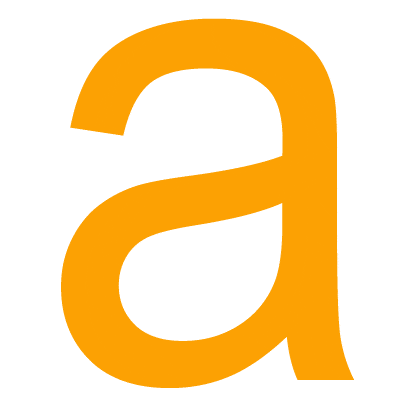
Arial (Sonora Sans)Uma família de fontes sem-serifa, de qualidade inferior. É conhecida entre os designers gráficos pela sua semelhança com um tipo famoso, a Helvetica.Sendo a Helvetica uma letra de estética bem árida, a Arial consegue ser uma cópia inferior da Helvetica. Supostamente, a Arial foi inspirada no desenho de uma outra fonte, a Hass Grotesk, (que também serviu de inspiração ao desenho da Helvetica). Esta fonte foi desenvolvida como uma fonte bitmap sem-serifa por Robin Nicholas e Patricia Saunders em 1982 nos escritórios da empresa Monotype no Reino Unido. A IBM já havia usado uma fonte similar, a Helvetica, adquirida à Linotype, na impressora IBM 4250. Mas talvez pelos elevados custos de licenciamento da fonte Helvetica, pediram então à Monotype para desenvolver uma fonte sem serifa, e metricamente igual à Helvetica para efeitos de compatibilidade, a ser incluída numa nova série de impressoras a laser (IBM 3800). A Monotype criou uma fonte, baseada numa já existente, a Monotype Grotesk, mas metricamente semelhante à Helvetica, assim como, subtis alterações quanto à forma e ao espaçamento entre letras, de forma a ser mais legível em monitores com más resoluções.
Nesta altura, a IBM denominou-a "Sonora Sans" (e a Times New Roman por "Sonora Serif"). Uns anos mais tarde, a Microsoft lança o Windows v 1.0 em 1985. Desde essa data até ao lançamento do Windows 3.0, a Microsoft inclui nestas versões a fonte "Helv" (assim como a "TmsRmn"), sofrendo então um processo em tribunal devido à violação de marca ("Helv" é abreviação de "Helvetica", "TmsRmn" da "Times New Roman"). A Microsoft procura então uma fonte que pudesse substituir a Helvetica, de forma a evitar elevados custos de licenciamento da Linotype (tal como a IBM havia feito) para o próxima versão do Windows. É aqui que entra a Monotype com a fonte Sonora, liçenciada à IBM, mas não em exclusivo. A Microsoft lança então em 1992, o Windows 3.1 com esta família de fontes da Monotype, denominando-a Arial, e sob o formato de uma nova tecnologia desenvolvida em parceria com a Apple, o TrueType. Surgiu assim, pela necessidade que a IBM tinha para concorrer com a fonte Helvetica, criada pela empresa Linotype em 1957, e muito popular desde então. Evitando assim o uso dessa fonte, devido aos elevados custos de licença por parte da Linotype e também da Adobe Systems, esta última detentora da tecnologia PostScript que a fonte Helvetica utilizava. O Windows 3.1 foi o primeiro sistema operativo a implementar esta tecnologia TrueType, com um conjunto de de outras fontes (Arial, Bookman Oldstyle, Book Antiqua, Corsiva, Century Schoolbook, Century Gothic e Times New Roman). Esta surgiu também com o intuito de ser uma alternativa economicamente viável em relação ao PostScript da Adobe Systems. LinksThe Scorge of Arial: http://www.ms-studio.com/articles.html Informações sobre a fonte Arial no site da Microsoft - em inglês http://www.microsoft.com/Arial |